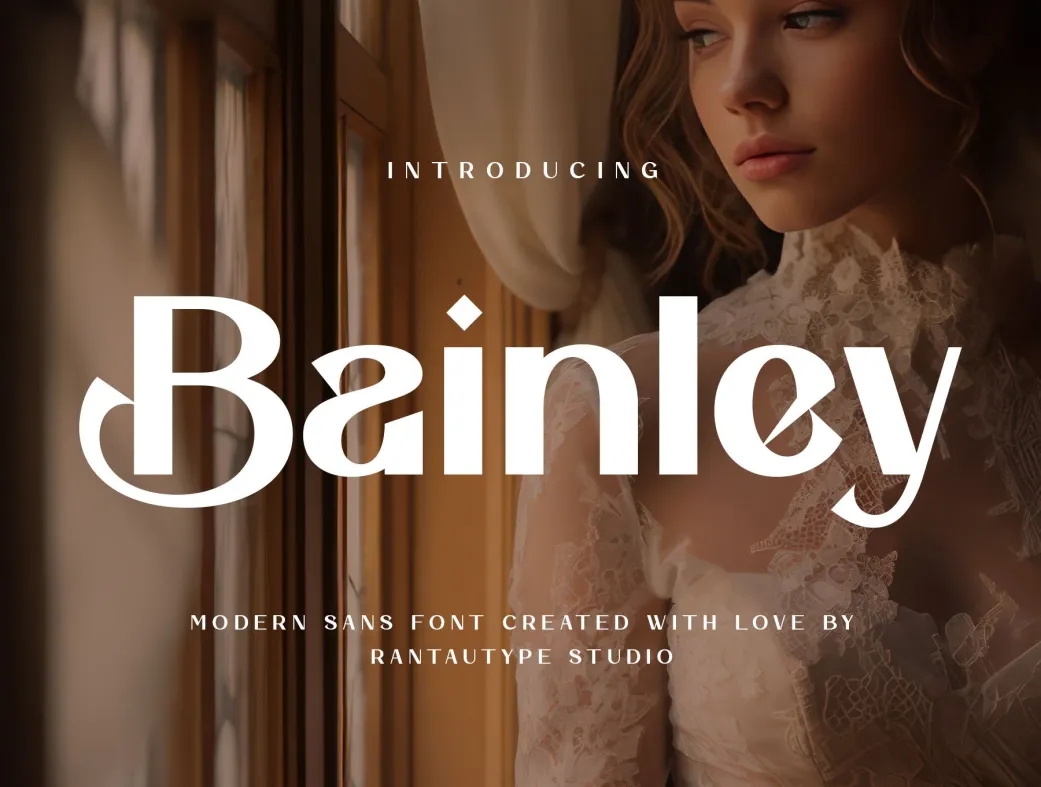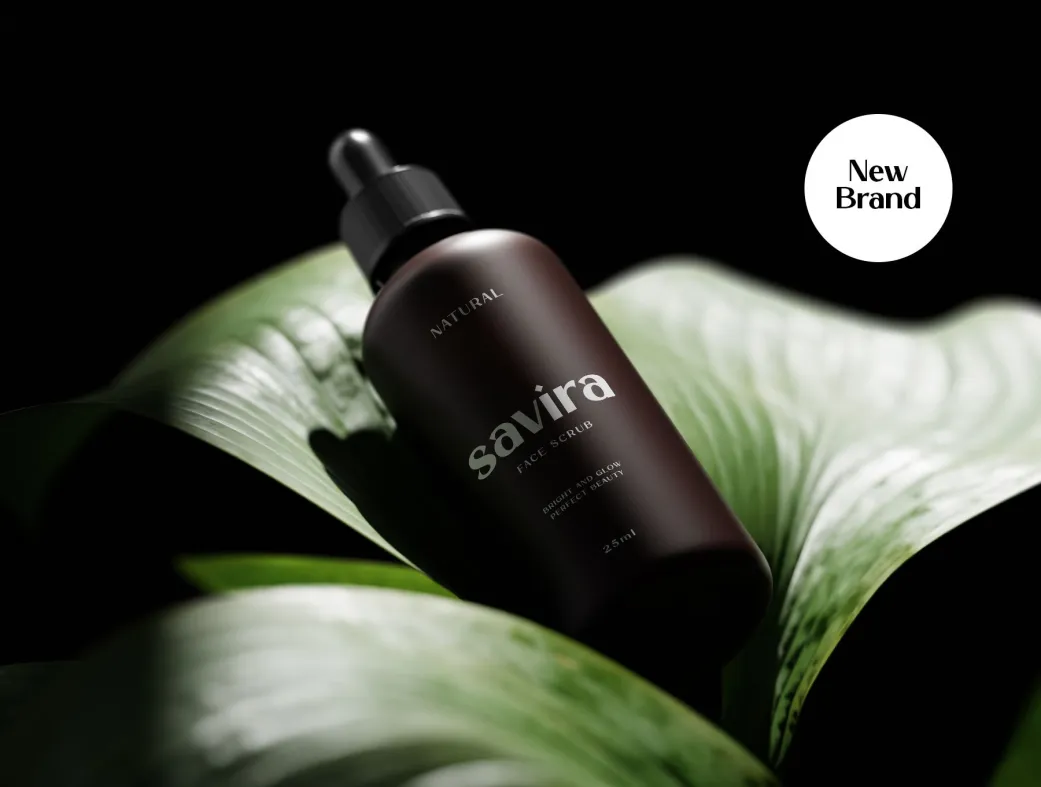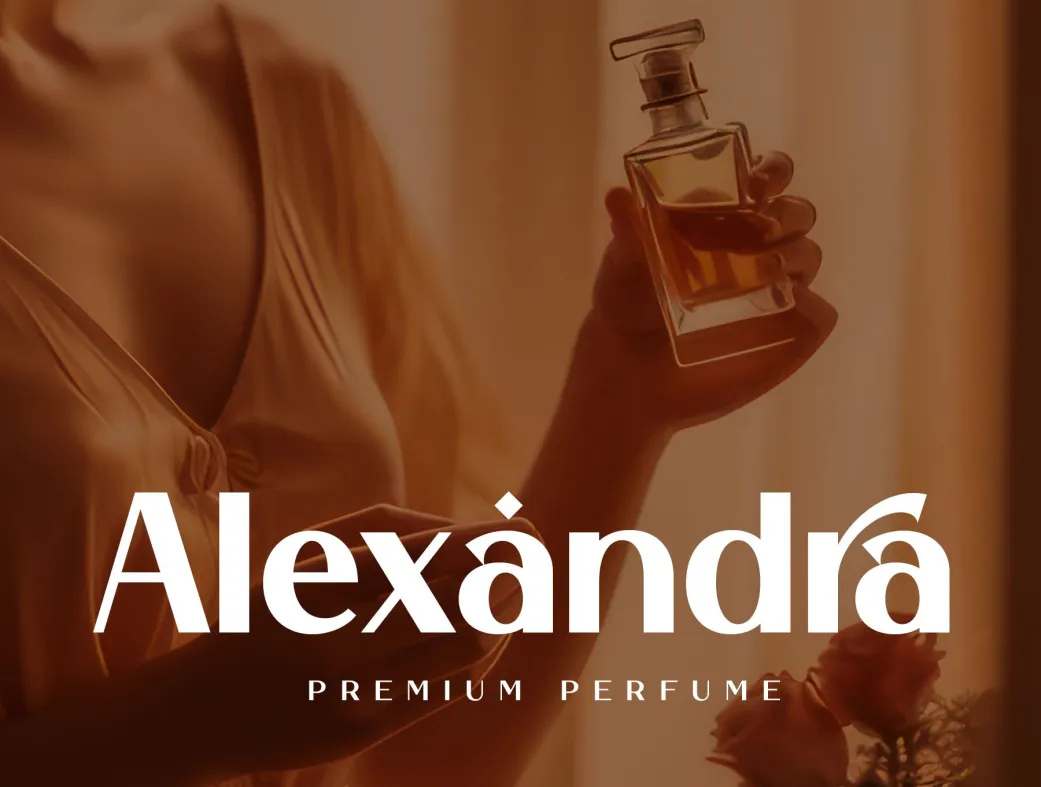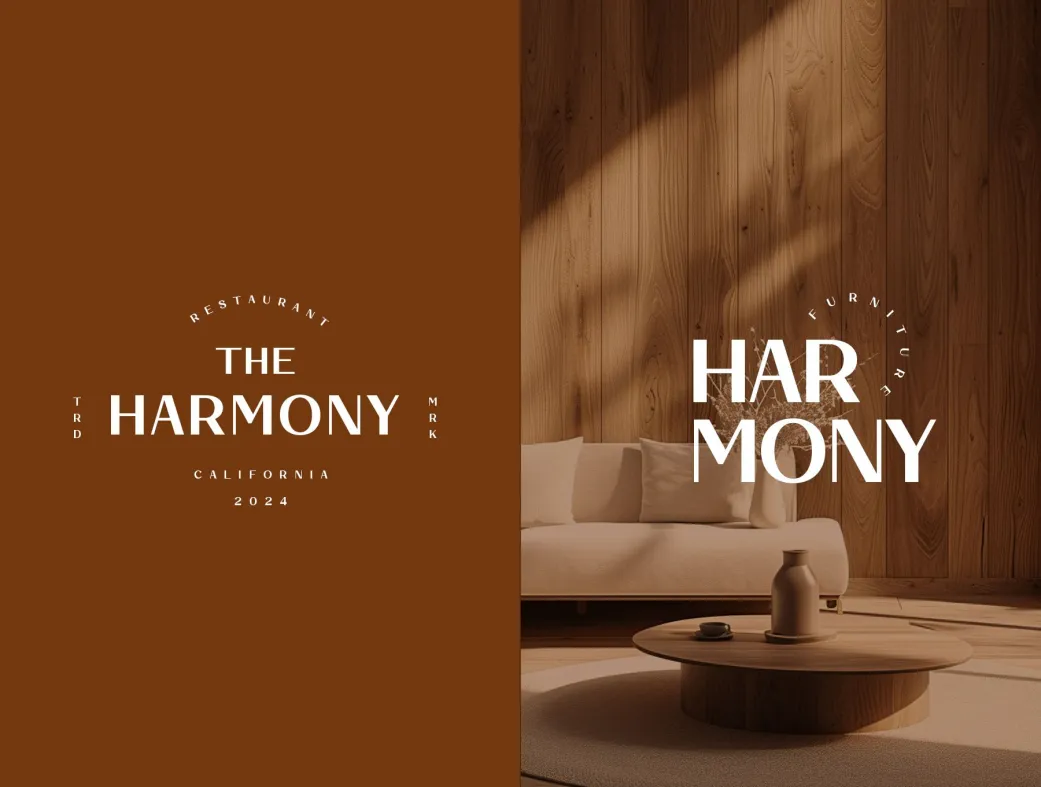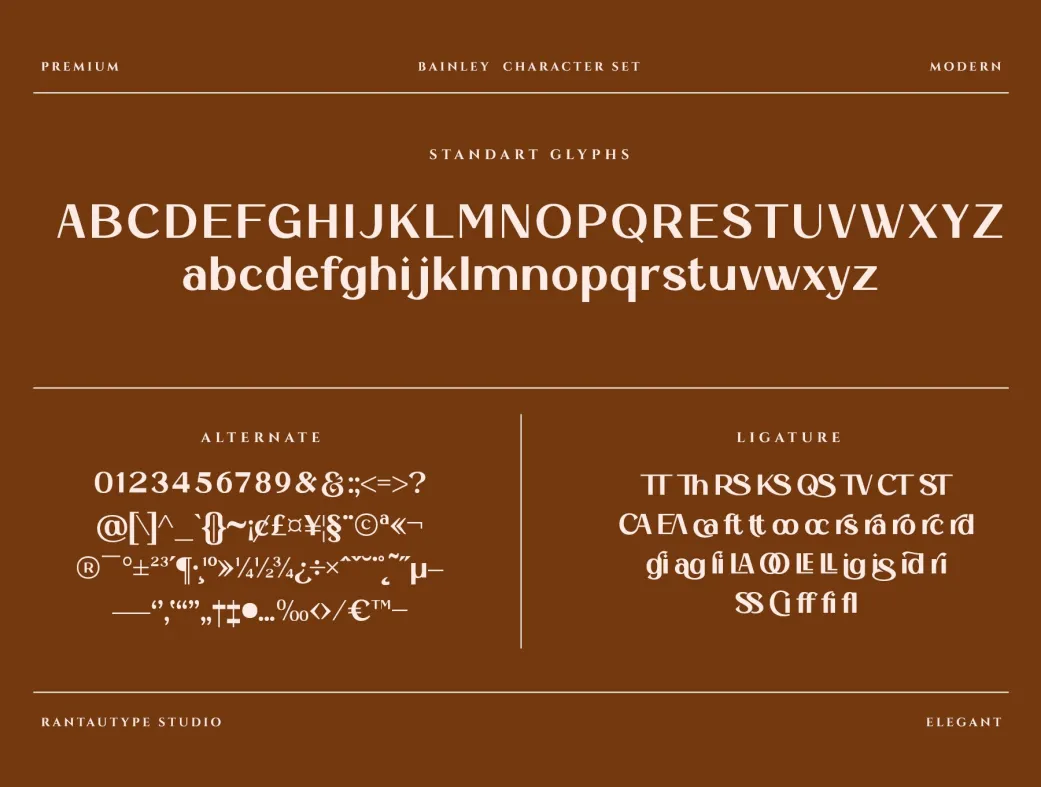
فونت زنانه مدرن باینلی | Bainley
با فونت زنانه مدرن باینلی، طراحی‌های شیک و خلاقانه‌تان را به نمایش بگذارید!
Bainley Modern Feminine Typeface
فونت زنانه مدرن باینلی | Bainley | Bainley Modern Feminine Typeface
فونت زنانه مدرن باینلی (Bainley) یک نوع خط سنس با سبک لوکس و شیک است که به شما امکان می‌دهد ایده‌های خلاقانه‌تان را به شکلی زیبا و جذاب به نمایش بگذارید. این فونت با ویژگی‌های متنوع خود، انتخابی ایده‌آل برای پروژه‌های طراحی مدرن و زندگی روزمره شماست.
فونت باینلی شامل دو نسخه‌ی عادی و ایتالیک (OTF/TTF/WOFF) است که به راحتی قابل استفاده در نرم‌افزارهای مختلف طراحی مانند Adobe Illustrator، Photoshop و InDesign می‌باشد. این فونت دارای گلیف‌های استاندارد، کاراکترهای عددی و عملکردی، و همچنین گزینه‌های جایگزین و لیگاتور است که به شما این امکان را می‌دهد تا طراحی‌های منحصر به فردی ایجاد کنید.
فونت باینلی به عنوان یک انتخاب عالی برای طراحی لوگو، تبلیغات، واترمارک در عکاسی، ایستگاه‌های اداری، پروژه‌های برندینگ، مجلات و دعوت‌نامه‌ها عمل می‌کند. به کاربران حرفه‌ای و مبتدی توصیه می‌شود از این فونت در پروژه‌های طراحی خود استفاده کنند تا یک حس شیک و لوکس به کارهای خود ببخشند.
1. فونت باینلی برای چه نوع پروژه‌هایی مناسب است؟
• فونت باینلی برای پروژه‌های طراحی مدرن، لوگو، تبلیغات، و برندینگ بسیار مناسب است و به طراحی‌های شما ظاهری شیک و لوکس می‌بخشد.
2. آیا فونت باینلی از چند زبان پشتیبانی می‌کند؟
• بله، این فونت از کاراکترهای چندزبانه پشتیبانی می‌کند و برای زبان‌های مختلفی مانند انگلیسی، اسپانیایی، آلمانی و بسیاری دیگر قابل استفاده است.